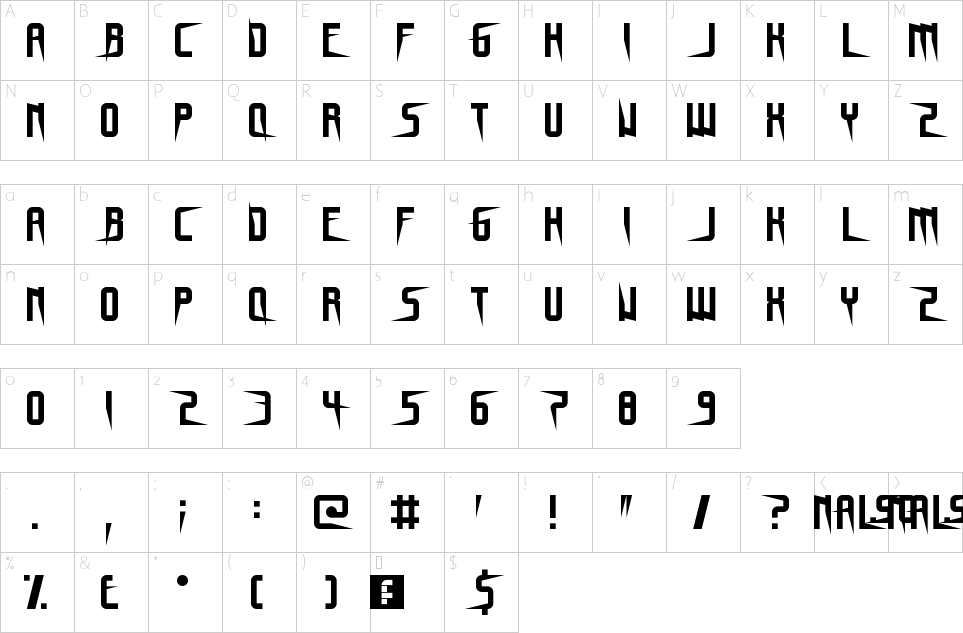
A fonte Gnome Splinters é uma opção versátil para designers que buscam uma abordagem diferente e divertida aos seus projetos. Desenhada pela Chequered Ink, esta font foi desenvolvida para oferecer um toque único e criativo. Com sua aparência irregular e surpreendente, a Gnome Splinters traz ao seu trabalho um ar de experimentação e originalidade que pode impressionar seus destinatários. A font está disponível gratuitamente tanto para Windows quanto para Mac, tornando-a uma excelente escolha para quem busca opções únicas sem comprometer a praticidade ou a qualidade. Em um mundo cada vez mais digitalizado, não há nada como encontrar algo diferente e divertido que pode destacar seu trabalho entre a multidão de outros designers digitais. Descubra por si mesmo o prazer de experimentar Gnome Splinters para sua próxima peça de design.